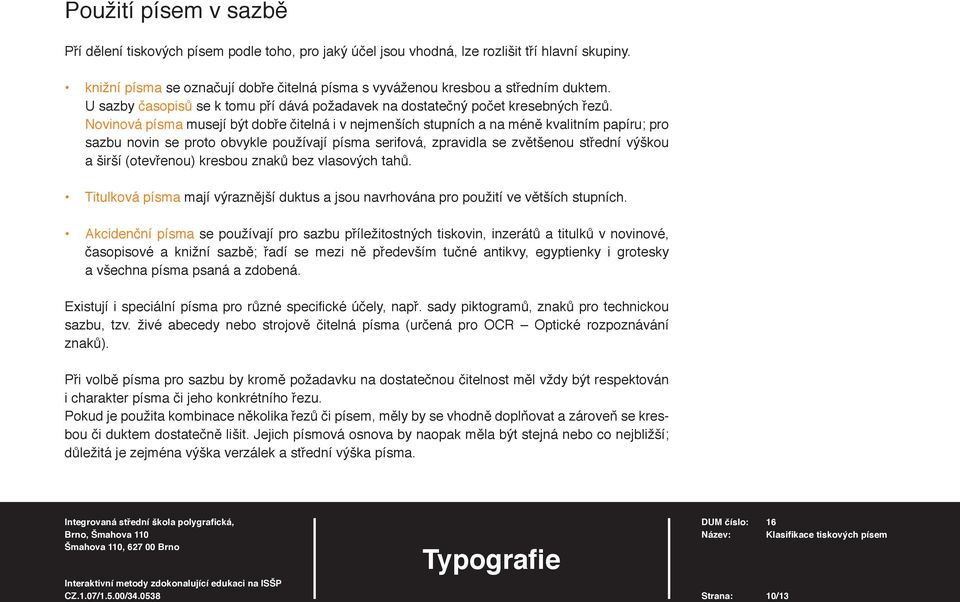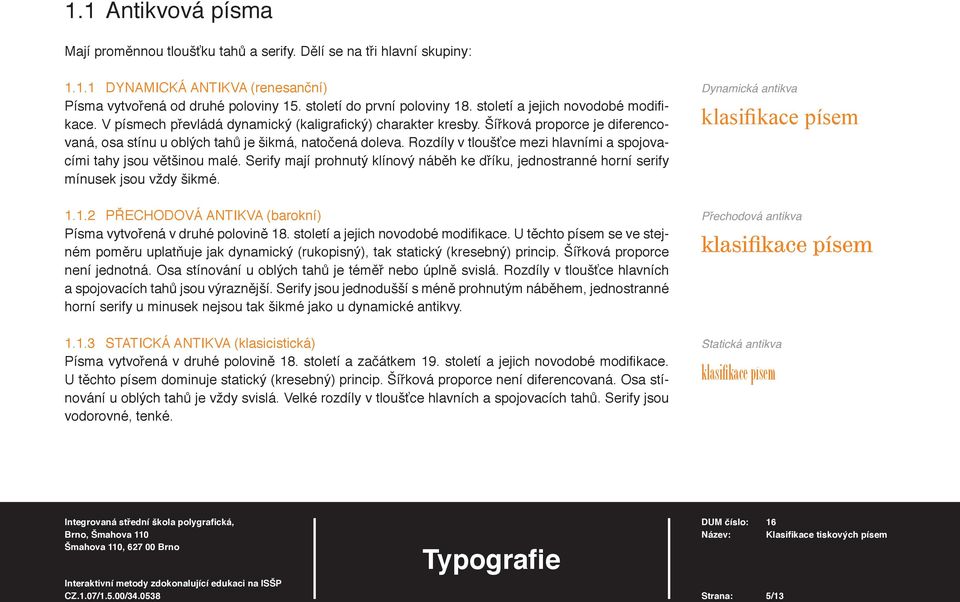
16. Klasifi kace tiskových písem. Typografie
3 Od vynálezu knihtisku v 15. století vzniklo velké množství tiskových písem; v digitální podobě jich v současnosti existuje již několik desítek tisíc. Pro orientaci při nakupování písem nebo při rozhodování, jaké písmo použít pro sazbu, je proto nezbytná nějaká klasifi kace, která existující písma rozděluje do menších skupin na základě vhodných společných vlastností. Při práci s písmy různého charakteru je při jejich třidění do menších skupin dobré vycházet z klasifi - kace tiskových písem vytvořené v druhé polovině 20. století českým typografem Janem Solperou. Tato klasifi kace respektuje historický vývoj písma a specifi kuje typické prvky tvarů písmových znaků. Základní rozdělení písem latinková písma nelatinková písma pravosměrná (slovanská, řecká) nelatinková písma levosměrná (orientální) ostatní písma (exotická) Strana: 3/13
4 1 Latinková písma 1.1 Antikvová písma Dynamická antikva (renesanční) Přechodová antikva (barokní) Statická antikva (klasicistická) 1.2 Lineární písmo serifové 1.3 Lineární písmo bezserifové statické Lineární písmo bezserifové dynamické Lineární písmo bezserifové geometricky konstruované Lineární antikva 1.4 Kaligrafi cká písma 1.5 Volně psaná písma 1.6 Lomená písma Strana: 4/13
5 1.1 Antikvová písma Mají proměnnou tloušťku tahů a serify. Dělí se na tři hlavní skupiny: DYNAMICKÁ ANTIKVA (renesanční) Písma vytvořená od druhé poloviny 15. století do první poloviny 18. století a jejich novodobé modifi - kace. V písmech převládá dynamický (kaligrafi cký) charakter kresby. Šířková proporce je diferencovaná, osa stínu u oblých tahů je šikmá, natočená doleva. Rozdíly v tloušťce mezi hlavními a spojovacími tahy jsou většinou malé. Serify mají prohnutý klínový náběh ke dříku, jednostranné horní serify mínusek jsou vždy šikmé PŘECHODOVÁ ANTIKVA (barokní) Písma vytvořená v druhé polovině 18. století a jejich novodobé modifi kace. U těchto písem se ve stejném poměru uplatňuje jak dynamický (rukopisný), tak statický (kresebný) princip. Šířková proporce není jednotná. Osa stínování u oblých tahů je téměř nebo úplně svislá. Rozdíly v tloušťce hlavních a spojovacích tahů jsou výraznější. Serify jsou jednodušší s méně prohnutým náběhem, jednostranné horní serify u minusek nejsou tak šikmé jako u dynamické antikvy STATICKÁ ANTIKVA (klasicistická) Písma vytvořená v druhé polovině 18. století a začátkem 19. století a jejich novodobé modifi kace. U těchto písem dominuje statický (kresebný) princip. Šířková proporce není diferencovaná. Osa stínování u oblých tahů je vždy svislá. Velké rozdíly v tloušťce hlavních a spojovacích tahů. Serify jsou vodorovné, tenké. Dynamická antikva klasifikace písem Přechodová antikva klasifikace písem Statická antikva klasifi kace písem Strana: 5/13
6 1.2 Lineární písmo serifové Lineární písma jsou charakteristická nevýrazným, někdy úplně chybějícím stínováním. V průběhu 19. a 20. století vzniklo několik typů lineárních písem; dělit je lze např. podle způsobu zakončení tahů. LINEÁRNÍ PÍSMO SERIFOVÉ egyptienka (19. století) Lineární serifová písma jsou typická výraznými deskovitými serify a převážně nediferencovanou šířkovou proporcí s uzavřeným tvarem znaků. Jejich střední výška je zpravidla zvětšená. U lineárního písma s rovnými serify jsou deskovité serify zcela bez náběhu a tloušťka tahů je většinou jednotná. Lineární serifové klasifikace písem Oproti tomu clarendon má deskovité serify s prohnutými náběhy a malý rozdíl v tloušťce hlavních a spojovacích tahů (osa stínování je svislá). Tato písma se používají častěji, a to zejména u novin a časopisů. Strana: 6/13
7 1.3 Lineární písmo bezserifové (grotesk) Jak napovidá už jeho název, má dva hlavní znaky je téměř nebo úplně bez stínování a jeho tahy nejsou zakončeny serify LINEÁRNÍ PÍSMO BEZSERIFOVÉ STATICKÉ (19. století) Až na nepřítomnost serifů je kresba jeho znaků příbuzná lineárnímu serifovému písmu má nediferencovanou šířkovou proporci, oblé tahy uzavírající tvar znaků a mírně diferencovanou tloušťku tahů se svislou osou stínování. V současnosti používané statické grotesky mají zvětšenou střední výšku. Lineární bezserifové statické klasifi kace písem LINEÁRNÍ PÍSMO BEZSERIFOVÉ DYNAMICKÉ (1. polovina 20. století) Tvarem znaků navazuje na renesanční antikvu. Šířková proporce dynamických grotesků je více či méně diferencovaná, mírně proměnná je i tloušťka tahů; tato písma mají univerzální využití. Lineární bezserifové dynamické klasifi kace písem LINEÁRNÍ PÍSMO BEZSERIFOVÉ GEOMETRICKY KONSTRUOVANÉ (1. polovina 20. st.) Kresba znaků je často odvozena z kruhu, ale existují i písma odvozená z jiného geometrického tvaru. TIoušťka tahů je až na výjimky jednotná; šířková proporce závisí na způsobu konstrukce znaků, častěji je nediferencovaná. Pro sazbu delších textů jsou použitelná pouze některá z těchto písem. Lineární bezserifové geometrické klasifi kace písem LINEÁRNÍ ANTIKVA (20. století) Jako lineární antikva jsou označována písma, u nichž se v různém poměru mísí kresebné prvky antikvy a lineárních písem. Mohou se tedy lišit mírou diferenciace šířkové proporce i tloušťky tahů. Jednotícím prvkem je to, že zakončení tahů je buď zřetelně rozšířené, nebo jsou tahy ukončeny malými, nevýraznými serify. Tím se lineární antikva odlišuje jak od klasické antikvy, tak od serifových i bezserifových lineárních písem. Lineární antikva klasifikace písem Strana: 7/13
8 1.4 Kaligrafi cká písma Vycházejí z kultivovaných kaligrafi ckých skriptů s výraznými rozdíly v tloušťce tahů. Dynamické navazuje na kaligrafi cká písma 16. a 17. století. Jeho forma je odvozena z kaligrafi e plochým perem, postaveným šikmo k účaří. Přechodové navazuje na kaligrafi cká písma z konce 17. a začátku 18. století. Je odvozeno z kaligrafi e plochým perem, postaveným rovnoběžně s účařím. Kaligrafi cká písma klasifi kace písem Statické navazuje na skripty z konce 18. a začátku 19. století. Vychází z kaligrafi e ostře seříznutým perem, kdy rozdílů v tloušťce tahů se dosahuje změnou tlaku na pružinu pera. Volně kaligrafi cké je odvozeno z reklamních skriptů 20. století. Vychází z kaligrafi e kreslené štětcem. Strana: 8/13
9 1.5 Volně psaná písma Vycházejí ze současných rukopisných skriptů. U většiny těchto písem jsou v tloušťce nepatrné rozdíly. Jsou psána kulatým a tupým nástrojem. Volně psaná klasifikace písem 1.6 Lomená písma Písma, která se vyvíjela od období gotiky až do 19. století. Např. Švabach, Rotunda...atd. Lincoln Lomená písma klasifi kace písem Strana: 9/13
10 Použití písem v sazbě Pří dělení tiskových písem podle toho, pro jaký účel jsou vhodná, lze rozlišit tří hlavní skupiny. knižní písma se označují dobře čitelná písma s vyváženou kresbou a středním duktem. U sazby časopisů se k tomu pří dává požadavek na dostatečný počet kresebných řezů. Novinová písma musejí být dobře čitelná i v nejmenších stupních a na méně kvalitním papíru; pro sazbu novin se proto obvykle používají písma serifová, zpravidla se zvětšenou střední výškou a širší (otevřenou) kresbou znaků bez vlasových tahů. Titulková písma mají výraznější duktus a jsou navrhována pro použití ve větších stupních. Akcidenční písma se používají pro sazbu příležitostných tiskovin, inzerátů a titulků v novinové, časopisové a knižní sazbě; řadí se mezi ně především tučné antikvy, egyptienky i grotesky a všechna písma psaná a zdobená. Existují i speciální písma pro různé specifi cké účely, např. sady piktogramů, znaků pro technickou sazbu, tzv. živé abecedy nebo strojově čitelná písma (určená pro OCR Optické rozpoznávání znaků). Při volbě písma pro sazbu by kromě požadavku na dostatečnou čitelnost měl vždy být respektován i charakter písma či jeho konkrétního řezu. Pokud je použita kombinace několika řezů či písem, měly by se vhodně doplňovat a zároveň se kresbou či duktem dostatečně lišit. Jejich písmová osnova by naopak měla být stejná nebo co nejbližší; důležitá je zejména výška verzálek a střední výška písma. Strana: 10/13
11 Převedení textu na křivky Textové editory i sazbové nebo ilustrační programy umožňují modifi kovat vzhled vysázeného textu různými transformacemi. Tyto funkce by ale měly být využívány pouze v odůvodněných případech u krátkých textů a vždy by takový textový objekt měl být následně převeden do křivek, tedy změněn na obecný vektorový objekt. InDesign Illustrator menu Text > Vytvořit obrysy Potom již není možné běžně editovat text po obsahové stránce, ale je zajištěno, že výsledek nebude závislý na následném zpracování použitých fontů, transformací či efektů (nejčastěji jednotkou RIP). Strana: 11/13
12 Kontrolní otázky: 1. Rozděl a popiš antikvová písma. 2. Rozděl a popiš lineární písma. 3. Jaký je rozdíl mezi kaligrafi ckým a volně psaným písmem? Strana: 12/13